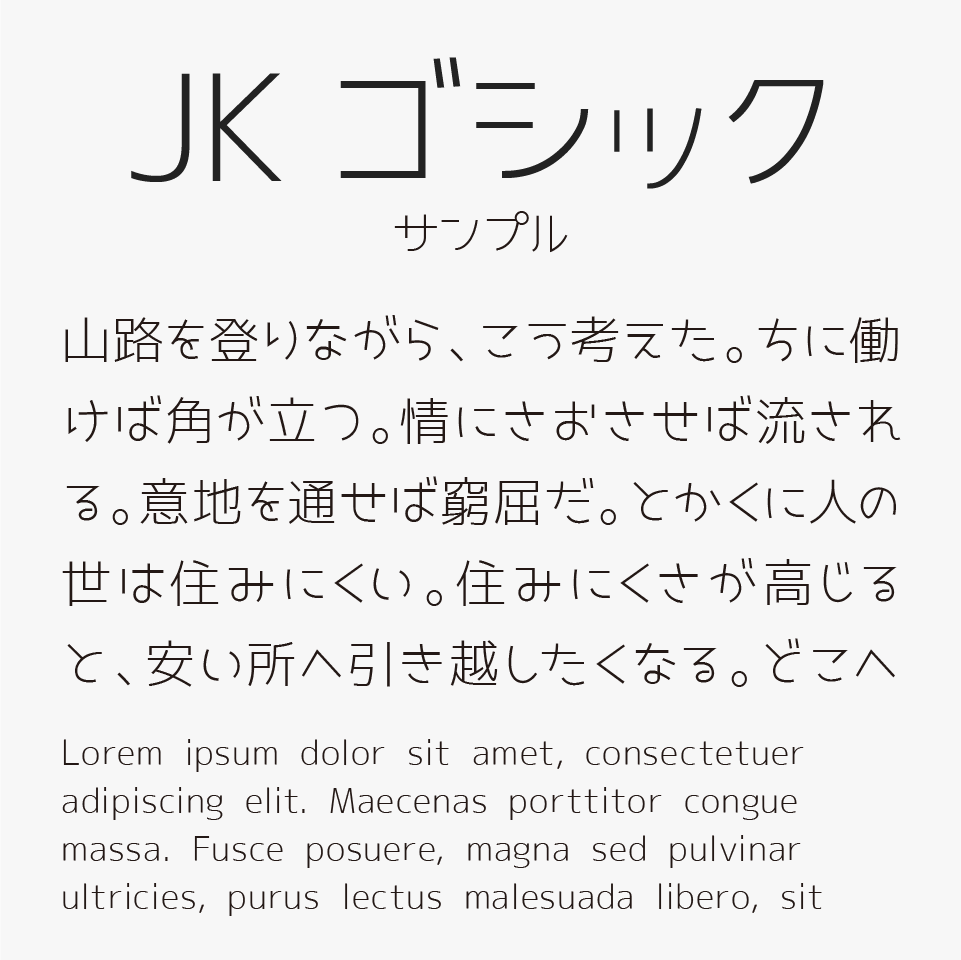
女子高生風 JKゴシック
JKゴシックフォントとは、女子高生が書いたような文字を意識した可愛らしい丸っこく、こじんまりとしたこぶりな文字が特徴のゴシック体フォントです。
一般的なゴシック体フォントと比べて、全体的に小ぶりで丸みのあるデザインに仕上げられているため、可愛らしさとやわらかさを感じられるゴシック体フォントとなっています。
堅苦しい印象のゴシック体ではなく、親しみやすくやわらかな雰囲気のゴシック体を探している方にもおすすめのフォントです。
ウェイトは、「JKゴシックL」と「JKゴシックM」の2種類が用意されています。
また、角丸加工を施した「JK丸ゴシック」という丸ゴシック版も用意されており、よりやわらかく親しみやすい雰囲気を楽しめるフォントとなっています。
収録文字は、ひらがな・カタカナ・数字・アルファベット・記号・漢字はオープンソースの「M+ FONTS」で補完させているので、一通りの文字には対応しています。